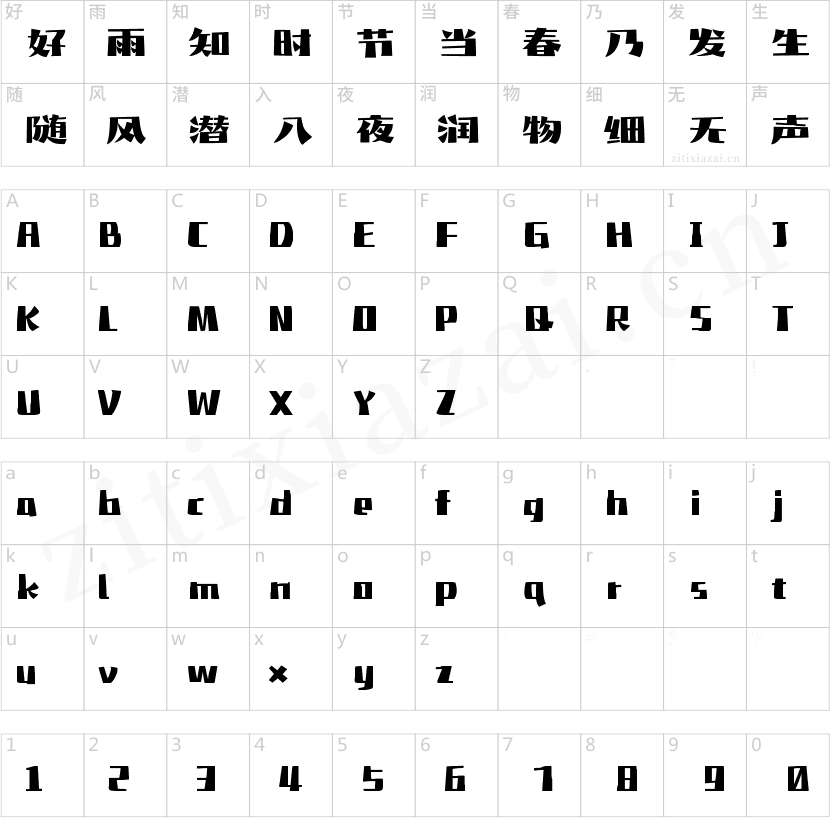
Aa芥末墩字体
Aa芥末墩是一款非常具有艺术性的字体,它的设计灵感来源于对古典艺术的研究,同时又融入了现代字体设计的元素。字形优美,笔画粗细变化自然,给人以大气、典雅的感觉。Aa芥末墩是一款既传统又现代的字体,它的设计充满艺术感,美观大方,实用性也非常强。无论是对于设计师还是对于普通读者来说,都是一种非常不错的字体选择。Aa芥末墩适合用于具有艺术感的场合,比如海报、宣传单张、书籍封面等。由于其字形流畅且具有动态感,也适合用于大量的文本排版,如报纸、杂志等。